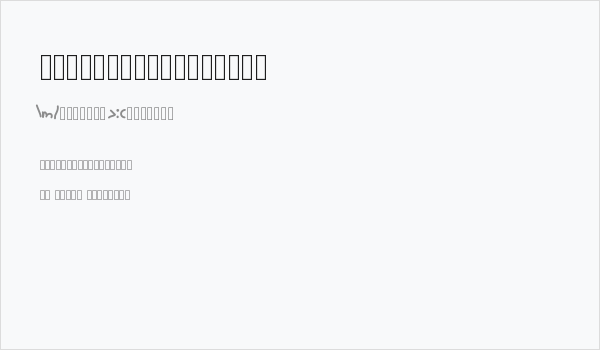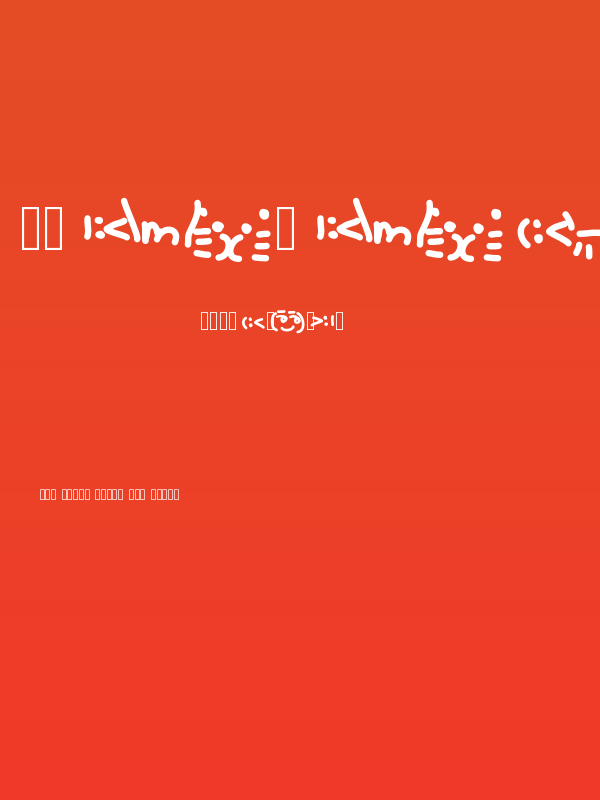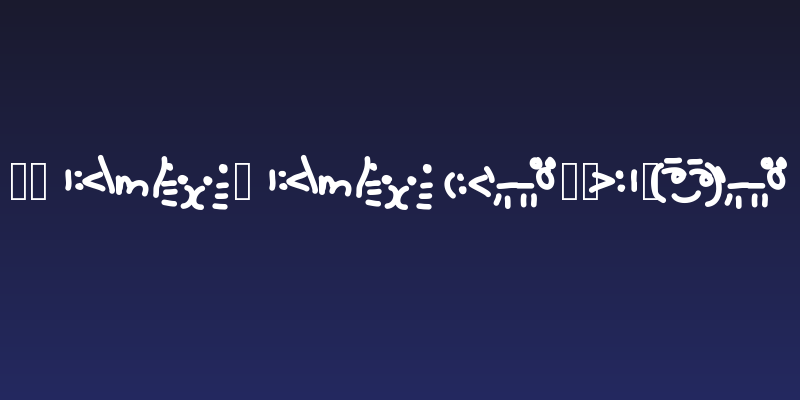
quickpickglyphsal Font
tricky
| Stile generale | Decorative, Playful, Whimsical |
| Caso d'uso | Headlines, Logos, Social media, Posters |
| Progetti proposti | Social media graphics, playful posters, meme creation, digital stickers, novelty greeting cards. |